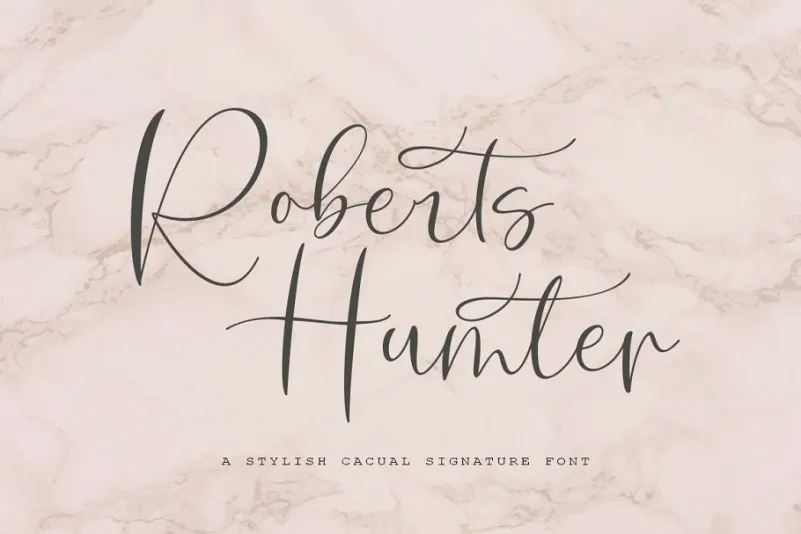
Roberts Humter Script Font – Fonte Grátis
Roberts Humter Script Font
Esta é uma fonte script moderna chamada Roberts Humter Font, criada pelo designer M.0Type. Ela oferece um toque elegante e suave para assinaturas de computador, mas também é versátil demais para se limitar a esse uso específico. Esta fonte script é perfeitamente adaptada para uma variedade de aplicações, incluindo marcas, cartões de visita empresariais, mensagens casuais, anúncios de revistas e publicações digitais. Os designers sempre procuram um equilíbrio entre modernidade e estilo pessoal no seu trabalho, e esta fonte atinge esse ponto de forma elegante e única. Os projetos que podem beneficiar da Roberts Humter Font são quase infinitos – seja para adicionar um toque pessoal aos seus cartões de visita ou para criar uma identidade visual forte em sua próxima campanha publicitária. Se você é um profissional que valoriza uma linguagem elegante e moderna, mas também deseja incorporar uma influência pessoal nos seus trabalhos, esta fonte vai definitivamente preencher esse vazio na sua coleção de ferramentas digitais. Experimente primeiro para ver a qualidade em ação antes de decidir por comprar.